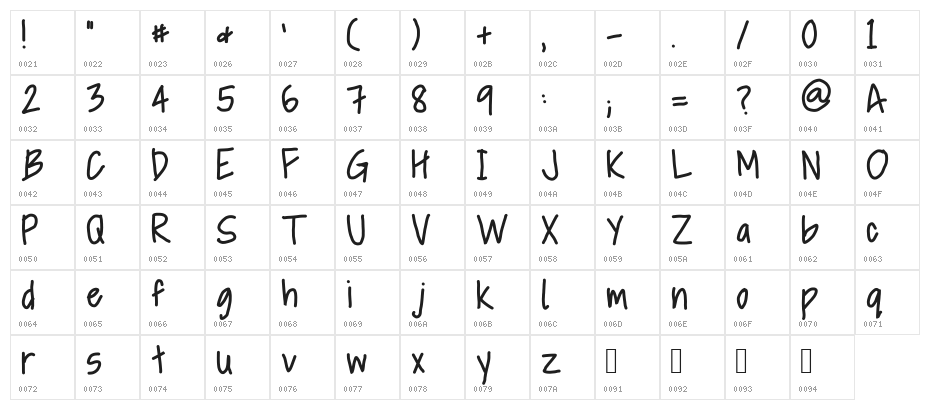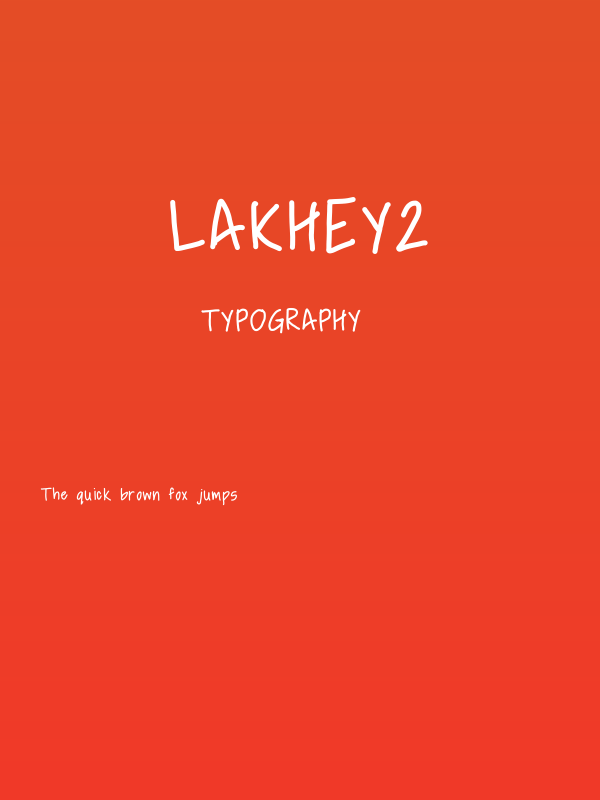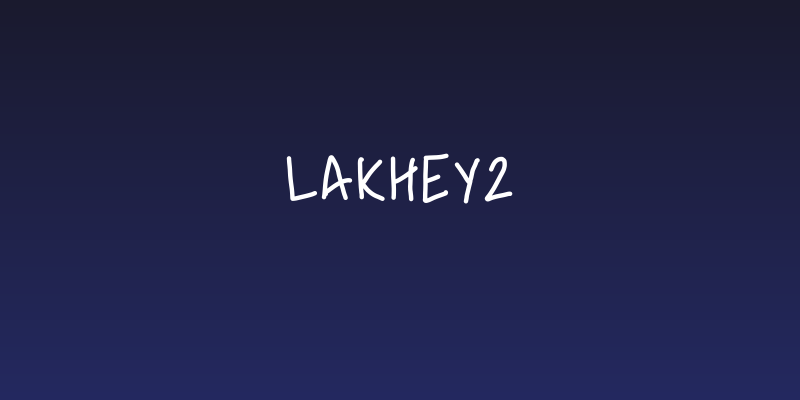
lakhey2 Font
| Stile generale | Casual, Playful |
| Caso d'uso | Headlines, Informal text, Creative projects |
| Progetti proposti | Ideal for greeting cards, children's books, casual branding, and social media graphics. |